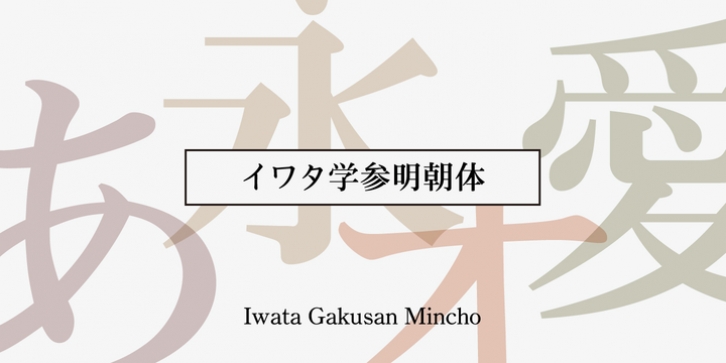
Iwata GMincho Pro was published by IWATA. Iwata GMincho Pro contains 2 styles and family package options.
教科書やå‚考書ã€å•題集ãªã©ã®æ•™è‚²æ•™æä½œæˆã®ãŸã‚ã«é–‹ç™ºã•ã‚ŒãŸæ˜Žæœä½“ã§ã™ã€‚
ç†ã‚„ペンã®å…¥ã‚Šã€æŠ¼ã•ãˆã€ãƒãƒã€ãƒˆãƒ¡ã€ç†é †ãªã©ã‚’ç†è§£ã—ã‚„ã™ã„よã†ãƒ‡ã‚¶ã‚¤ãƒ³ã—ã¦ã„ã¾ã™ã€‚